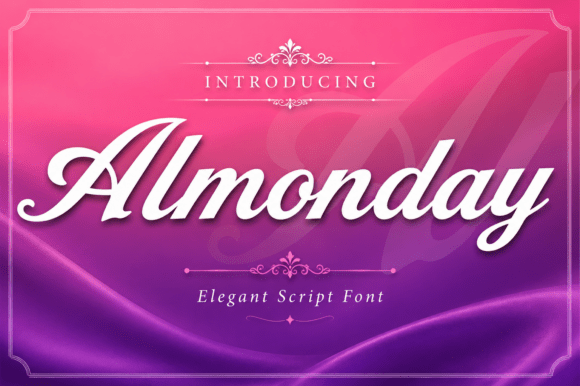
Almonday
การค้นหาองค์ประกอบการออกแบบที่เหมาะสมอาจเป็นเรื่องท้าทาย แต่ Almonday นำเสนอคอลเลกชันที่โดดเด่นซึ่งช่วยยกระดับงานของคุณได้ทันที
สร้างขึ้นอย่างแม่นยำ Almonday ให้เวกเตอร์ที่สะอาด พิมพ์ตัวอักษรที่ราบรื่น และใบอนุญาตเชิงพาณิชย์เพื่อความสบายใจ